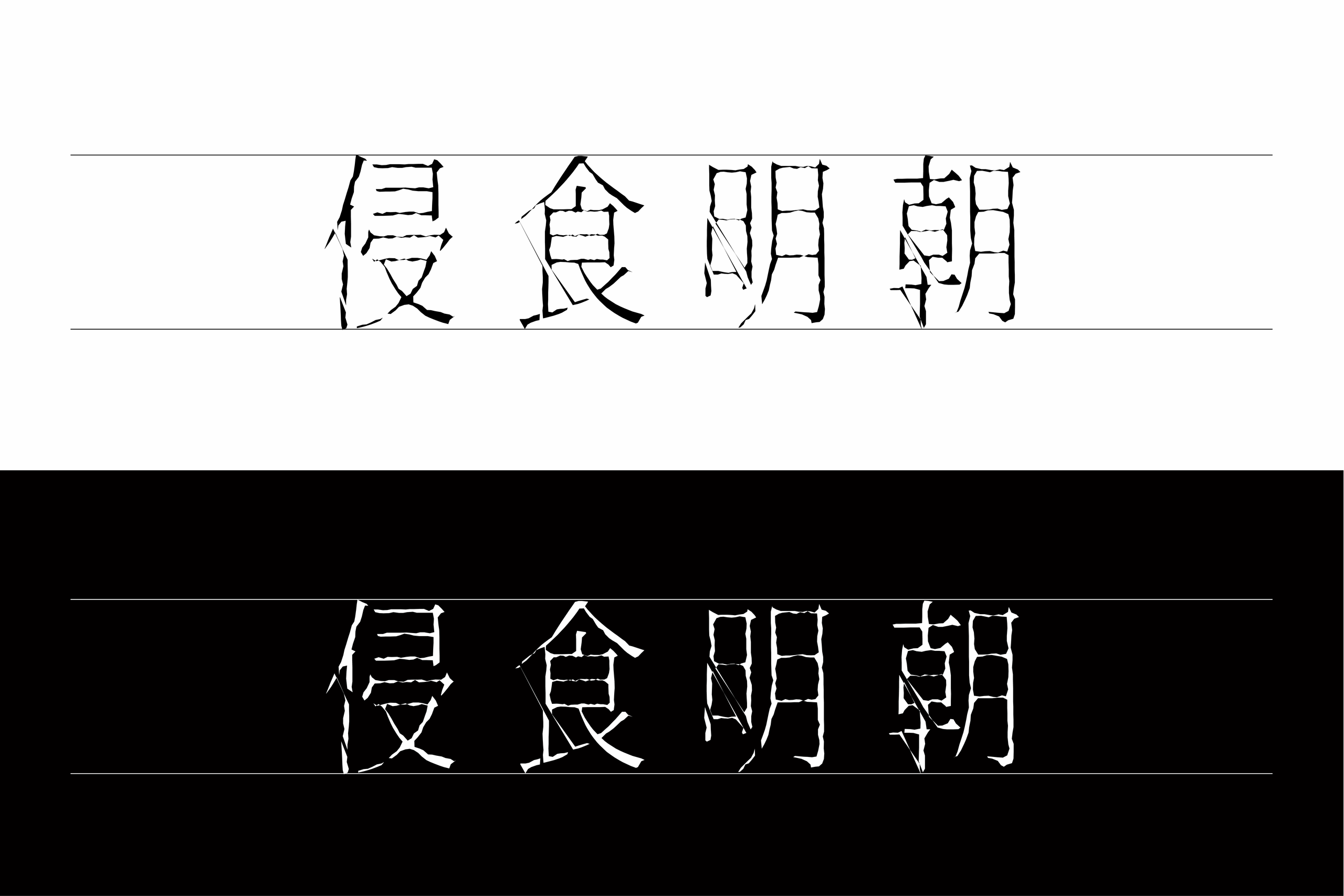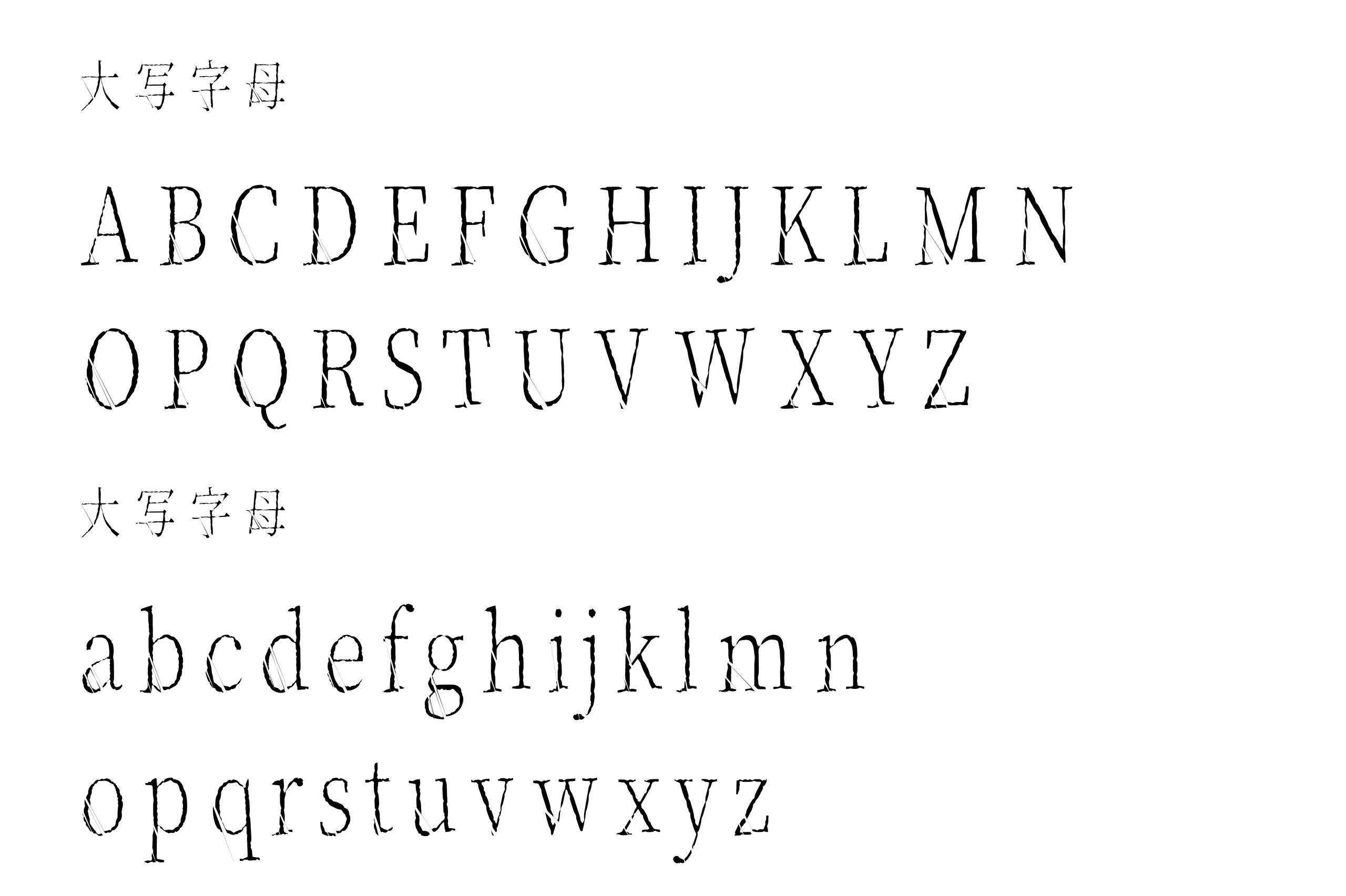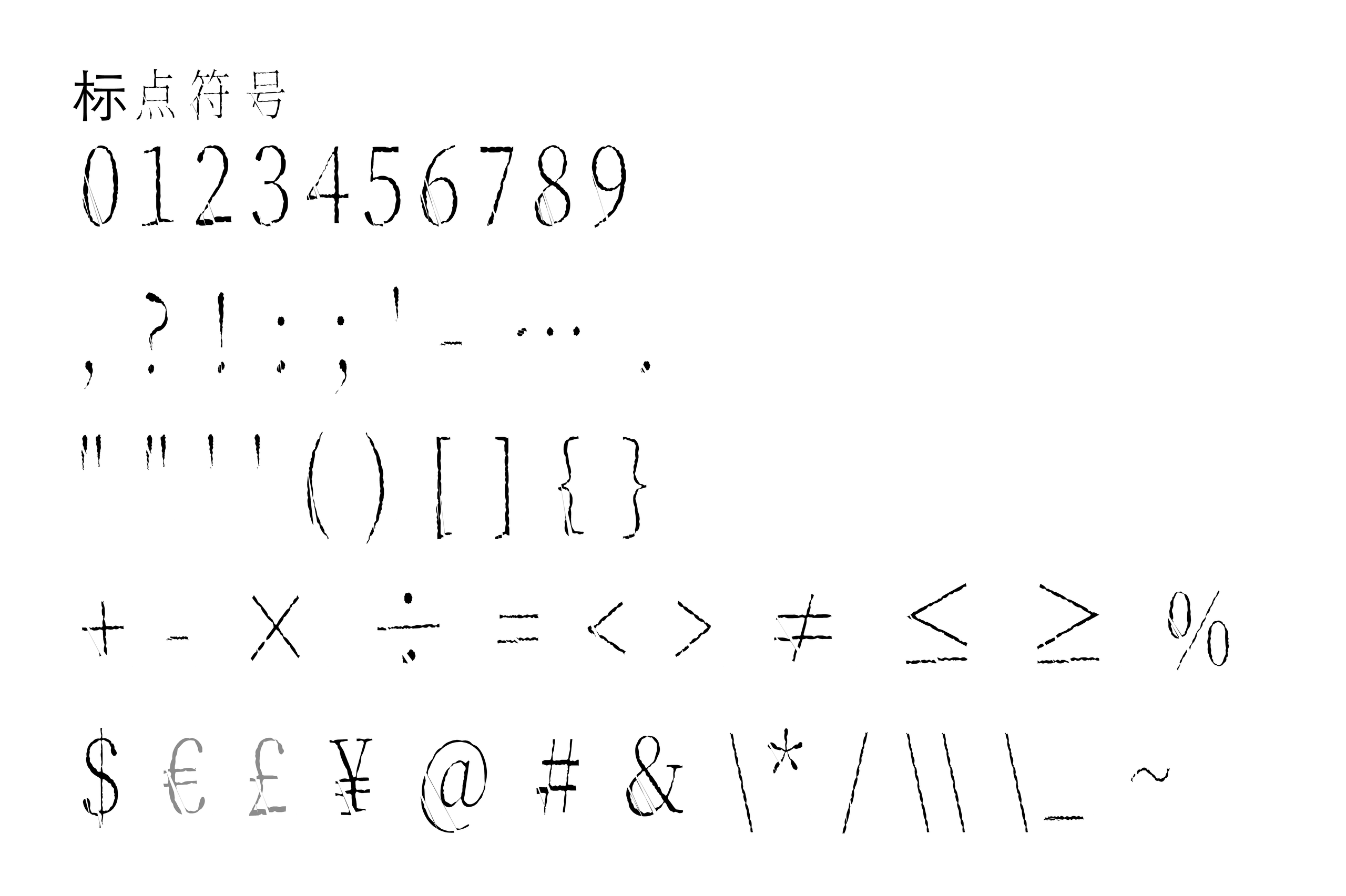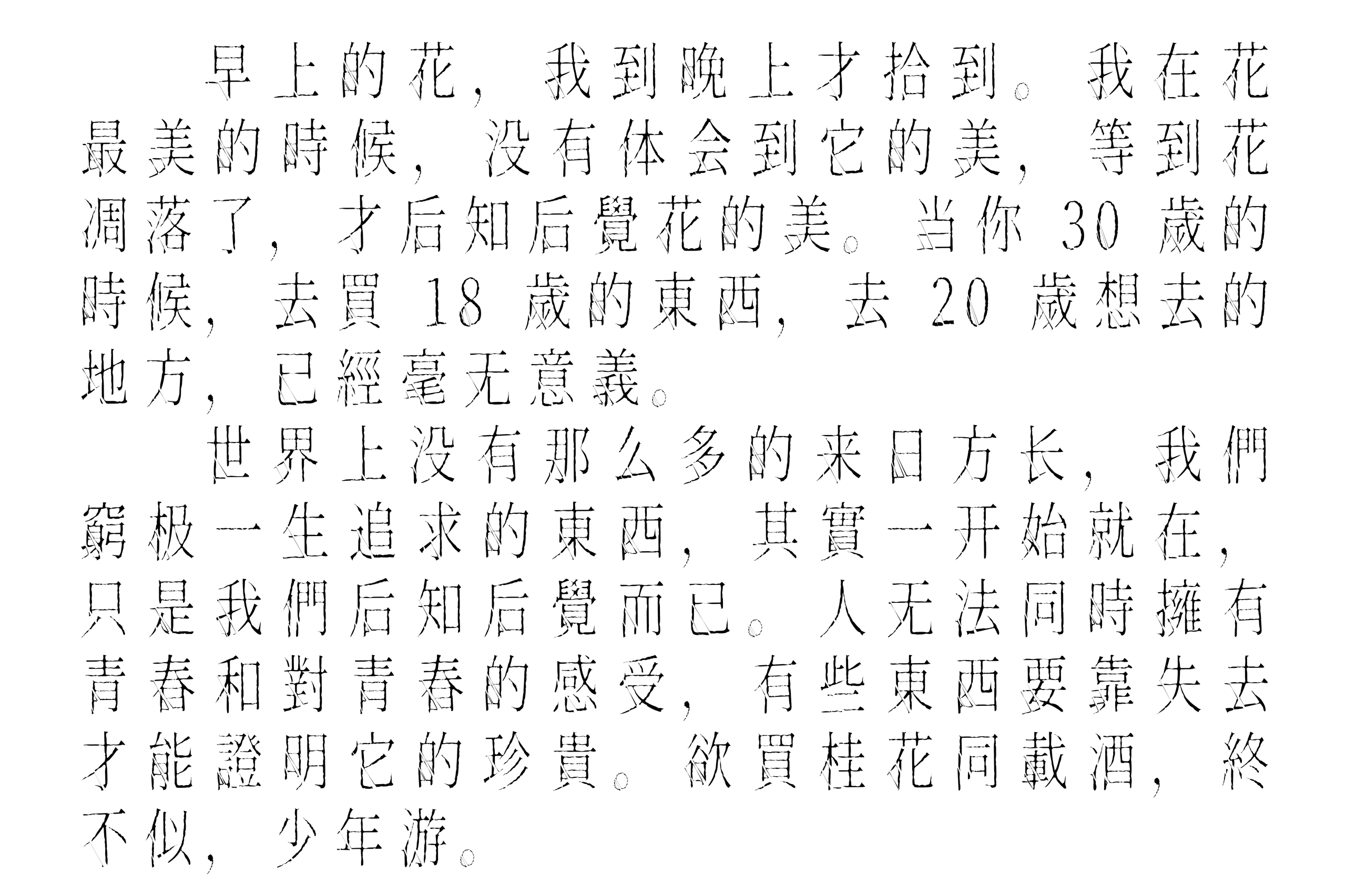
侵食明朝
侵食明朝(ShinsyokuMincho)是一款以源ノ明朝为基础进行再设计的日文字体,通过整体比例调整与字形细节处理,塑造出细长、锋利且带有明显侵蚀感的视觉风格。字体整体略带长体特征,文字向纵向延伸,使字面呈现出纤细而紧张的视觉效果,在保持明朝体基本结构的同时,也进一步强化了字体本身的个性与装饰性。
从字形细节来看,侵食明朝最具辨识度的特点在于其独特的裂痕、缺损与粗糙轮廓。字体并没有采用完整、平滑的笔画边缘,而是在文字轮廓中加入类似磨损、剥落和断裂的处理,使部分笔画仿佛经过长时间风化后逐渐失去完整形态。尤其在横竖笔画的连接处以及部分转折位置,可以看到较为明显的不规则缺口与裂纹效果,让文字呈现出一种脆弱、残缺却又具有视觉张力的质感。
这种设计使侵食明朝具有较强的退廃、冷峻与实验性气质。相比传统明朝体端正、优雅的字形表现,它更强调时间留下的痕迹与不完整之美,因此并不适合追求规整、稳定阅读体验的正文排版,而更适合作为具有氛围感的展示字体使用。例如电影海报、音乐视觉、游戏标题、悬疑或幻想类作品、艺术展览、品牌视觉以及视频封面等场景,都可以利用其细长的字形与破损质感营造出独特的视觉氛围。
侵食明朝同时提供了较为完整的西文字符、数字及常用标点符号,英文字母同样延续了纤细、修长并带有裂痕与磨损效果的设计语言,与中文字符能够形成统一的视觉风格。无论是英文标题、数字信息还是中英文混排,都能够保持较强的一致性。结合字体本身具有的纵向延展感与残缺边缘,在大字号排版中尤其容易形成鲜明的视觉焦点。
对于需要表现残缺、侵蚀、时间痕迹与冷峻氛围的设计项目来说,侵食明朝是一款具有较高辨识度的实验型明朝字体。它没有刻意追求字形的完美与规整,而是将裂痕和缺损转化为字体视觉语言,让文字在保留明朝体骨架的基础上,呈现出一种经过时间侵蚀后的独特美感。